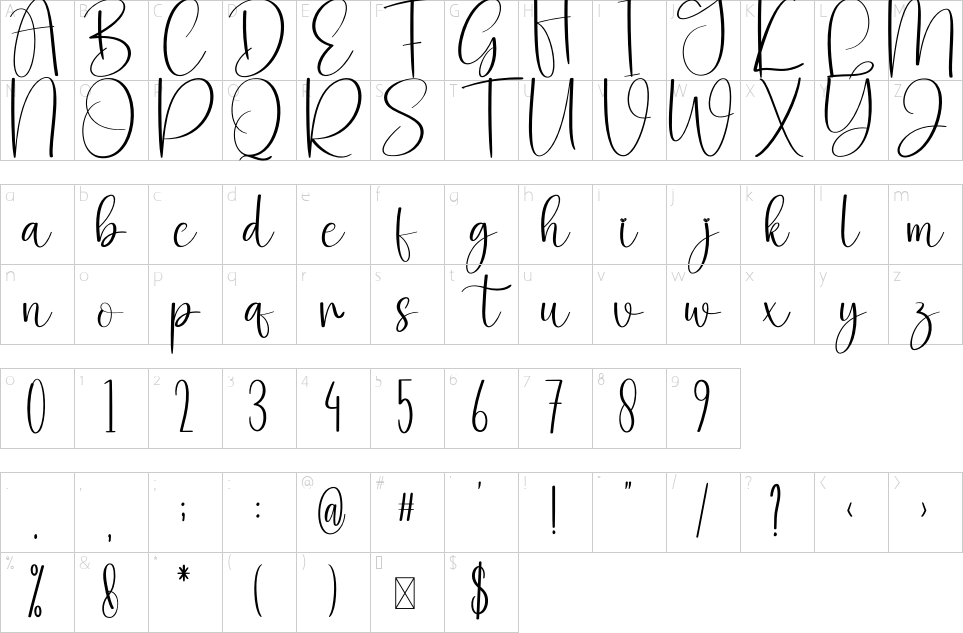
Descubra Delightful Font, uma elegante e alegre escolha para seus projetos digitais. Desenvolvida por william jhordy, essa fonte é perfeita tanto para aqueles que buscam um toque fresco e colorido em suas criações quanto para designers que valorizam uma solução de texto confortável. Com seu design agradável e moderno, Delightful Font traz vida aos seus projetos. Desenvolvida especialmente para usuários da plataforma Windows e Mac, Delightful Font está disponível gratuitamente para download. Após sua instalação, você encontrará facilmente as ferramentas necessárias para integrar Delightful Font em suas produções digitais, seja ela um site pessoal, uma publicação de blog ou até mesmo como fonte para seus designs gráficos. Convidamos todos a experimentar Delightful Font e explorarem essa maneira linda de dar vida aos seus projetos.